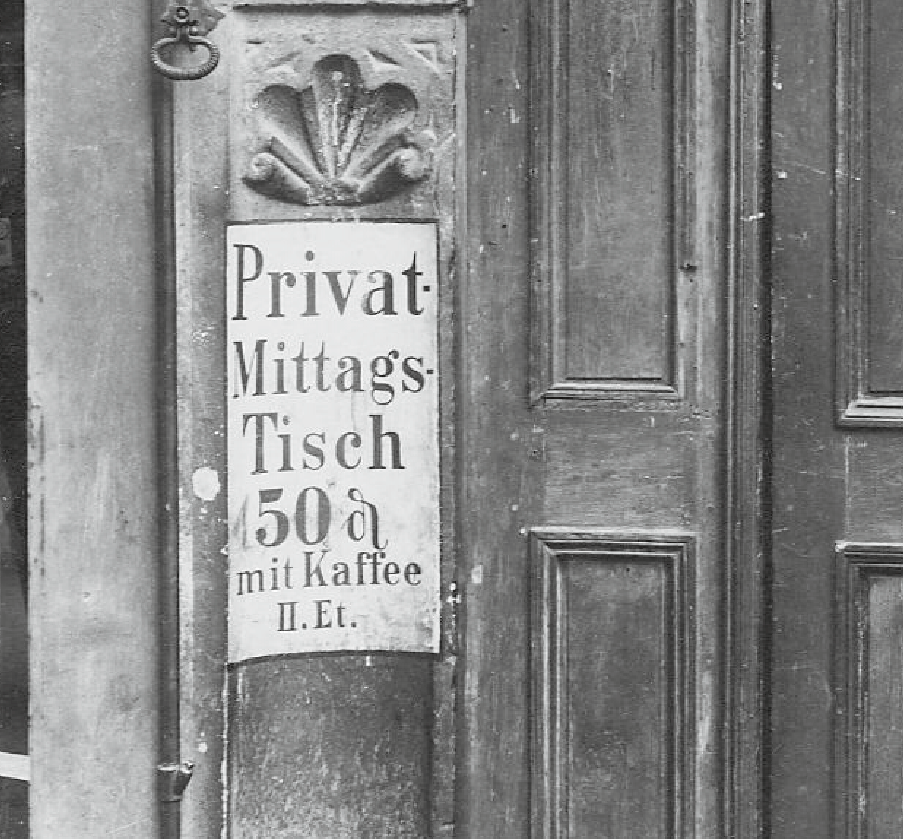
Altes Zeichen um 1900
Hallo zusammen, ich bin neu hier und hab mich gleich mal getraut eine Frage an euch zu stellen. Weiß jemand was dies für ein Zeichen nach "Privat-Mittags-Tisch 50…" heißt? Ich könnte mir vorstellen ob es ein Zeichen für Pfennig ist, aber ich bin mir nicht sicher. Die alte Schriftmalerei war in Leipzig um 1900.
Hallo und willkommen, eine tolle Frage und ein tolles Fundstück hast du ja gleich mitgebracht :nicken:
Pfennig sieht ja eigentlich so aus:
Vielleicht ist das ja eine kreative Varation, die sich der Maler ausgedacht hat :-?
Wenn man aber bedenkt, dass dieses Zeichen laut Wikipedia aus einem d entstanden ist, ist das gezeigte Zeichen gleich viel nachvollziehbarer. Vor allem, wenn man an gebrochene Schriften denkt.
»Pfennigzeichen wurde bis nach dem Zweiten Weltkrieg verwendet. Es war, wie nebenstehende Abbildung zeigt, ein in der deutschen Kurrentschriftgeschriebenes „d“ mit einem Schwung nach unten.«
Das gezeigte ist das "alte runde", üblicherweise zusammen mit Frakturschrift verwendet.
Oben steht zwar:
zusammen mit gedruckter Frakturschrift und Sütterlin-Handschrift:
aber unten wird es dann doch mit ›lateinischer Schrift‹ verwendet:
Schade, dass es nicht mehr gebraucht wird – hat irgendwie mehr Charme als ¢
Und ich freue mich, solche Fundstücke zu sehen.
Übrigens war noch bis Mitte der 1970er Jahre  das Pfund- und Pfennigzeichen besonders auf Wochenmärkten noch häufig zu sehen, zumeist mehr oder weniger von der Form abweichend, die man in alten Druckschriften finden konnte
Ich habe das z.B. auch nicht genannt, weil sich einfach aus dem Kontext ergibt, das der Mittagstisch wohl kaum 50 mal gelöscht werden soll.
Wenn mich jemand fragen wurde, was das Zeichen ⌘ auf einem Verkehrs-Wegweiser bedeutet, hätte ich auch nicht gesagt, das bedeutet "Command"
Ich frage mich dann schon manchmal, warum ich jetzt zum Blumenkohl fahren soll, wenn ich das in freier Schildbahn sehe ... :hammer:
Und ich frage mich manchmal, was wäre gewesen, hätten die Nazis dieses Zeichen auf diesem Stein in einer  germanischen Kultstätten gesehen, und dann dieses zu ihrem Zeichen gemacht, ob wir dann wohl ein Swastika auf der Command-Taste hätten?
Das skriptiv ausgebildete d steht für »denarius«, die lat. Entsprechung für Pfennig. Wie schon angemerkt wurde: das deleatur-Zeichen beim Korrekturlesen ist im Grunde die gleiche Glyphe.